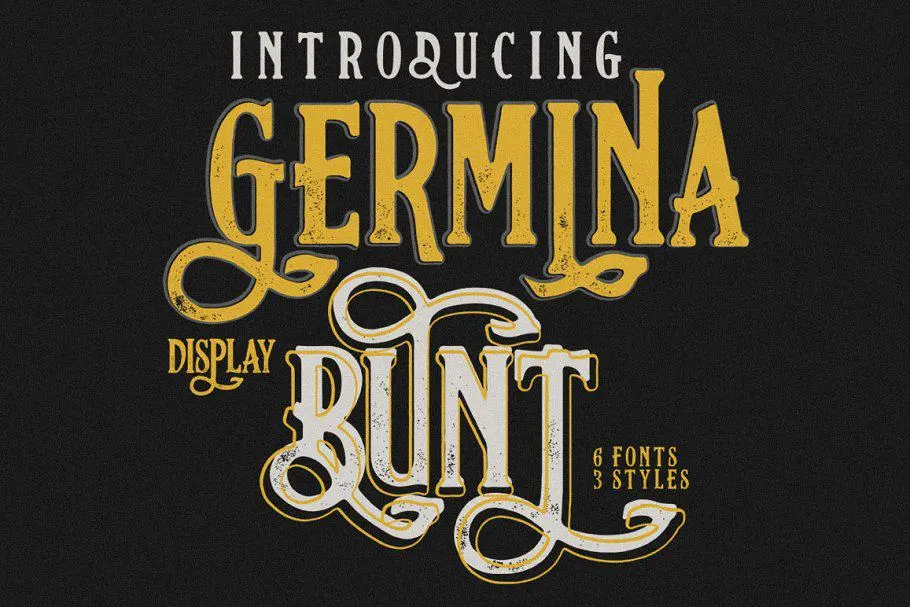
Germinabunt Typeface – Fonte Grátis
Germinabunt Typeface
Fonte Germinabunt é perfeita para quem busca algo distintivo entre as linhas do Blackletter Fonts. Seja para projetos modernos ou clássicos, esta fonte oferece um toque de criatividade indispensável para seu arsenal de design. Com suas letras escritas a mão e caracteres alternativos, Germinabunt é ideal tanto para revistas e embalagens quanto para websites, cabeçalhos de cartazes, cartões de aniversário, assinaturas de carta e diversos outros projetos criativos. Seja você um designer apaixonado por estilo moderno ou alguém que aprecia a elegância vintage, Germinabunt é uma ótima escolha para transformar seus materiais em algo único e memorável. Não perca tempo, invista no seu arsenal de fontes com Fonte Germinabunt.